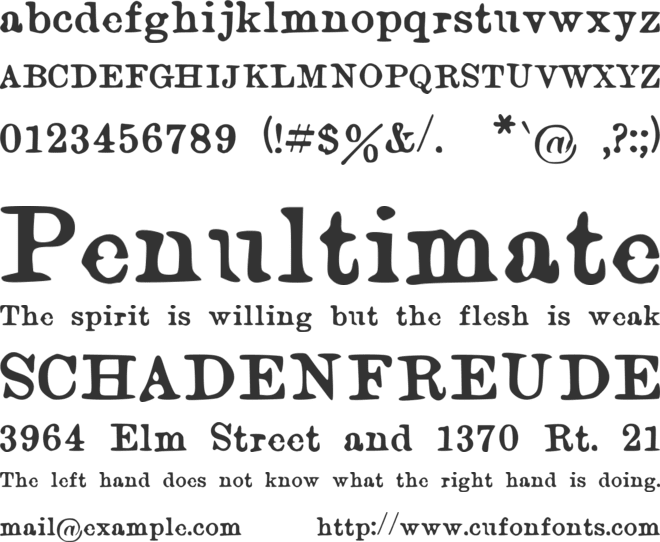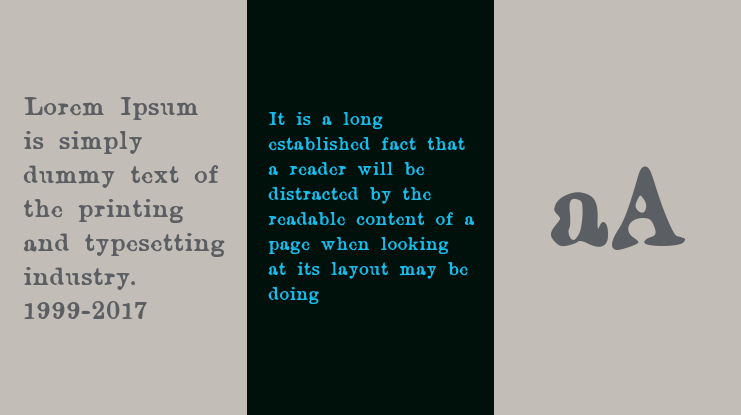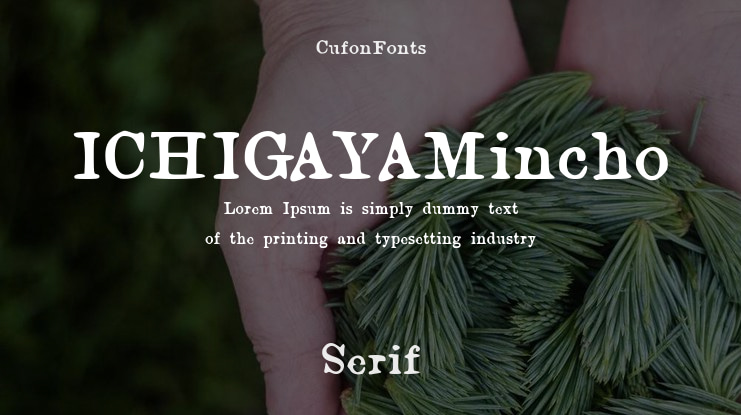
ICHIGAYAMincho Font
Based on the type specimens of Dai Nippon Printing Co. Ltd.
Most of the glyphs were quoted from "the 5 Point Serif Font Type Specimens", (1913, owned by Ichigaya no Mori: Hon to Katsuji-kan)
大日本印刷の前身企業である秀英舎活版製造所の活字をフォントにしました。
大部分が市谷の杜 本と活字館所有の「明朝五号活字摘要録」(1913)を基にしております。
一部の文字は「活字注文用当用漢字表」(1946)や
活版見本帖 Type Specimens(仮)(1914)を基にしております。